Garamond, Claude
Claude Garamond ist ein französischer Schriftschneider und Typograf. Geboren um 1498/99 in Paris, Frankreich. Gestorben 1561 in Paris. Schüler des Pariser Humanisten, Graveurs und Typografen Antoine Augereau (um 1485-1534), dem »Drucker der Königin Marguerite von Navarra«, bei dem Claude Garamond um 1510 eine Lehre als Buchdrucker in der Druckwerkstatt von Henri Estienne begann. Alternative Schreibweise seines Namens: Claude Garamont.
1530 schnitt Claude Garamond vermutlich für den französischen Typografen, Verleger und Lexikograf Robert Estienne (um 1499/1503–1559) unter dem Eindruck der Cicero- und Augustea-Schnitte seines Lehrmeisters Augereau – Stanley Morison (1889–1967) bezeichnete 1957 Augereau als »… pioneer in Paris of typografy in Roman letter who deserves immortality« – und der Alphabetsammlung des »Champ-Fleury« seines Mentors Geoffroy Tory (Buchdrucker des französischen Königs, 1480–1533) eine eigene Cicero-Type, die fast hundert Jahre später, um 1620, unter dem Namen »Garamond« von Jean Jannon (1580–1658) nachgeschnitten und publiziert wurde.
1533 schuf Garamond eine Cicero im aldinischen Stil für Claude Chevallon (o.A.-1537), in dessen (später von der Witwe weitergeführten) Druckerei er bis 1540 tätig war. 1540 schnitt er auf im Auftrag des königlichen Ratgebers und Bibliothekars Pierre Duchâtel (um 1480-1552) für den französischen König François I. (1494–1547), den Bruder von Marguerite von Navarra ( 1492–1549), die »Grecs du Roy«, »die Griechischen des Königs«, inspiriert von den Manuskripten des Kreters Angelus Vergecius (Engel Vergèce, um 1505–1569), der zu dieser Zeit als königlicher Kalligraf und Bibliothekar in Fontainebleau wirkte. Die legendäre Schreibkunst dieses gelehrten Exilgriechen, den König François I. wohlwollend als »notre écrivain en grec« titulierte, wurde sogar noch bis in die Mitte des 20. Jahrhunderts im französischen Sprichwort »écrire comme un ange« kolportiert.
Die griechischen Typen fanden erstmals 1543 in der Bibelausgabe »O mirificam« des königlichen Druckers und Verlegers Robert Estienne Verwendung und festigten Claude Garamonds Ruhm als einer der handwerklich besten Stempelschneider Frankreichs. Die originalen Stempel dieser »Regis typi« befinden sich heute in der Nationaldruckerei in Paris; wobei anzumerken ist, dass es keinen Nachweis dafür gibt, dass tatsächlich Claude Garamond diese griechischen Buchstaben entworfen und geschnitten hat. Fachleute vermuten, dass die »Grecs du Roy« bereits von seinem Lehrmeister Antoine Augereau entworfen wurden, der, im Gegensatz zu Garamond, der griechischen Sprache in Wort und Schrift mächtig war, über die notwendigen Kontakte und die erforderliche Bildung verfügte. Antoine Augereau wurde (deshalb) 1534 in Paris auf dem Place Maubert von der katholischen Inquisition auf dem Scheiterhaufen mit seinen Büchern verbrannt. 1)
Ähnliche Schlußfolgerungen vertreten einige Fachleute, unter ihnen der New Yorker Schriftgestalter George Abrams (um 1919/1920–2001), die sogar die Hypothese vertreten, dass Schriften, die Claude Garamond vor 1540 zugesprochen werden, von seinem Lehrmeister stammen könnten; es sich jedoch zumindest um Kopien der Entwürfe von Antoine Augereau handeln müsse, die handwerklich von Garamond im Zuge des Nachschnitts optimiert wurden.
In der Druckerei seines ersten Schwiegervaters Pierre Gaultier, mit dessen Tochter Guillemette er bis zu ihrem Tod im Jahre 1550 verheiratet war, versuchte sich Claude Garamond von 1545 bis 1546 kurz auch als Verleger, weil ihm sein typografisches Metier als »Nestbauer und Honigträger« sprich: »als Handlanger von Buchhändlern zu wenig lukrativ schien«, wie er in seinem Vorwort zur Edition der »Meditatio pia et religiosa« des David Chambellan beklagt: »Je retirais vraiment peu de profit de mon travail qui est de sculpter et de fondre les types de lettre (…) Ceux qui savent seulement tailler les lettres ne progressent guère (…) Ils construisent le nid des librairs, ils leur apportent leur miel.«
Die Prosperität seiner eigenen Werkstatt in der Rue des Carmes, wo er gemeinsam mit seinem Kompagnon und Stempelschneider Guillaume Le Bé (1525–1598) auch etliche Lehrlinge ausbildete, wurde in späteren Jahren vor allem durch den Verkauf von Typenmatrizen römischer Schriften gesichert. Ab 1550 perfektionierte Garamond seine Antiqua-Lettern und entwickelte auf Anregung des Rektors der Sorbonne, Jean de Gagny (o.A.–1549), auch einen kursiven Schriftschnitt seiner Cicero von 1530, der späteren »Garamond«. Dieser kursive Schnitt gilt bis heute unter Schriftgestaltern als typografische Quintessenz ästhetischer Vollkommenheit.
Eine zweite Ehe ab 1551 mit der wohlhabenden Ysabeau Le Fèvre brachte ihm nebst mehreren Weingärten auch ein Haus in Paris in der noblen rue Saint Denis, wo er 1561 mit rund 63 Jahren starb. Nach Garamonds Tod ging ein kleiner Teil seines Typenrepertoires in den Besitz von Guillaume Le Bé und später in den der Imprimerie Royale über. Die meisten originalen Matrizen und Stempel wurden jedoch von Christophe Plantin (um 1520–1589), einem französisch-flämischen Typografen und Verleger aus Anvers erworben, sieben Antiqua-Serien auch vom Frankfurter Schriftgießer Jacques Sabon (um 1535–1580/1590), in der Folge Egenolff-Berner.
Die vor allem während des 17. Jahrhunderts oft kopierten Schriftschnitte von Claude Garamond (und/oder Antoine Augereau?) gelten bis heute als Inbegriff typografischer Ästhetik, Eleganz und Lesbarkeit. Bis zum Ende des Bleisatzes wurden deshalb auch Französische Renaissance-Antiquas als »Garamond Schriften« oder als »Renaissance-Antiquas im Sinne Garamonds« bezeichnet. Nach fast zweihundertjährigem Dornröschenschlaf wurden sie 1928 in der deutschen »Garamond Stempel« auf Basis der alten Specimen (Schriftmuster) aus der Frankfurter Schriftgießerei Egenolff-Berner, revitalisiert.
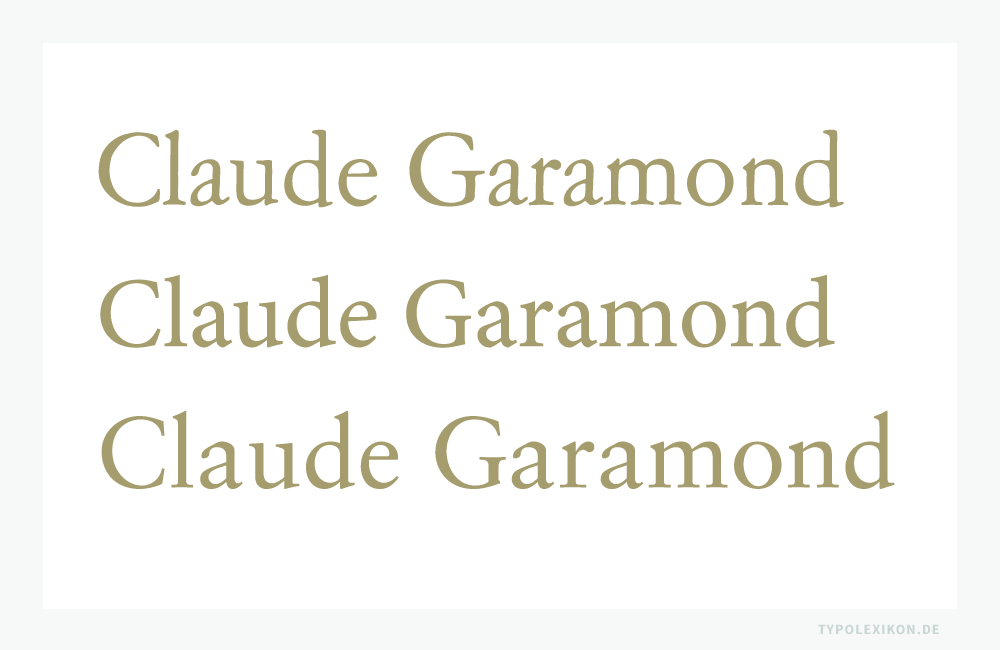
Viele Stempelschneider, Schriftgießer und Schriftgestalter (Type Designer) nahmen sich seitdem »die Garamond« für ihre eigene Schrift zur Vorlage. So auch Morris Fuller Benton (1872–1948) für seine Amsterdamer Garamond, Tony Stan (1917–1988) für seine ITC Garamond, Jan Tschichold (1902–1974) für seine Sabon und Robert Slimbach (* 1956) für seine Minion.
Nach Claude Garamond wurde auch das Mittel »Garamond« bennannt. 2) 3) 4) 5)
| ↑2 | Museumsempfehlung: Museum Plantin-Moretus, Vrijdagmarkt 22, 2000 Antwerpen. Dieses Museum besitzt die einzige komplette Serie von authentischen Garamond-Stahlstempeln, nach denen Robert Slimbach 1989/1991 die Adobe Garamond gestaltete. |